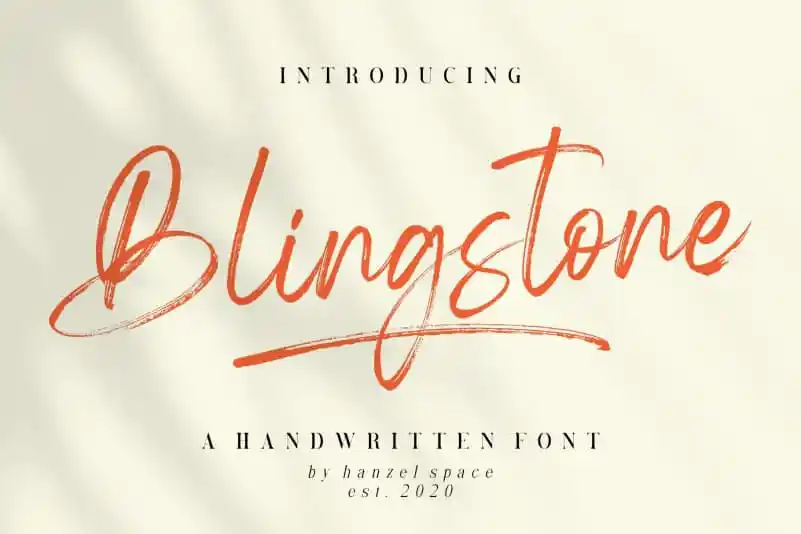
Blingstone Brush Font – Download Grátis
A Blingstone Brush Font é uma elegante fóntex feita à mão usando traço de pincel, trazendo um movimento natural e suave, perfeito para projetos criativos. Seu design apaixonado por sua forma livre e fluida cria uma sensação vibrante que certamente irá adicionar um toque único ao seu trabalho. Este tipo de fonte é especialmente apropriada para nomes, logotipos ou qualquer outro projeto onde desejas criar uma identidade visual ativa e deslumbrante. Com sua natureza suave e acolhedora, Blingstone Brush Font se adequa tanto à criação de arte digital quanto ao trabalho em impressão. Não importa o tipo de projeto que você esteja planejando, a garantia de uma aplicação criativa de alta qualidade está assegurada com essa fonte.